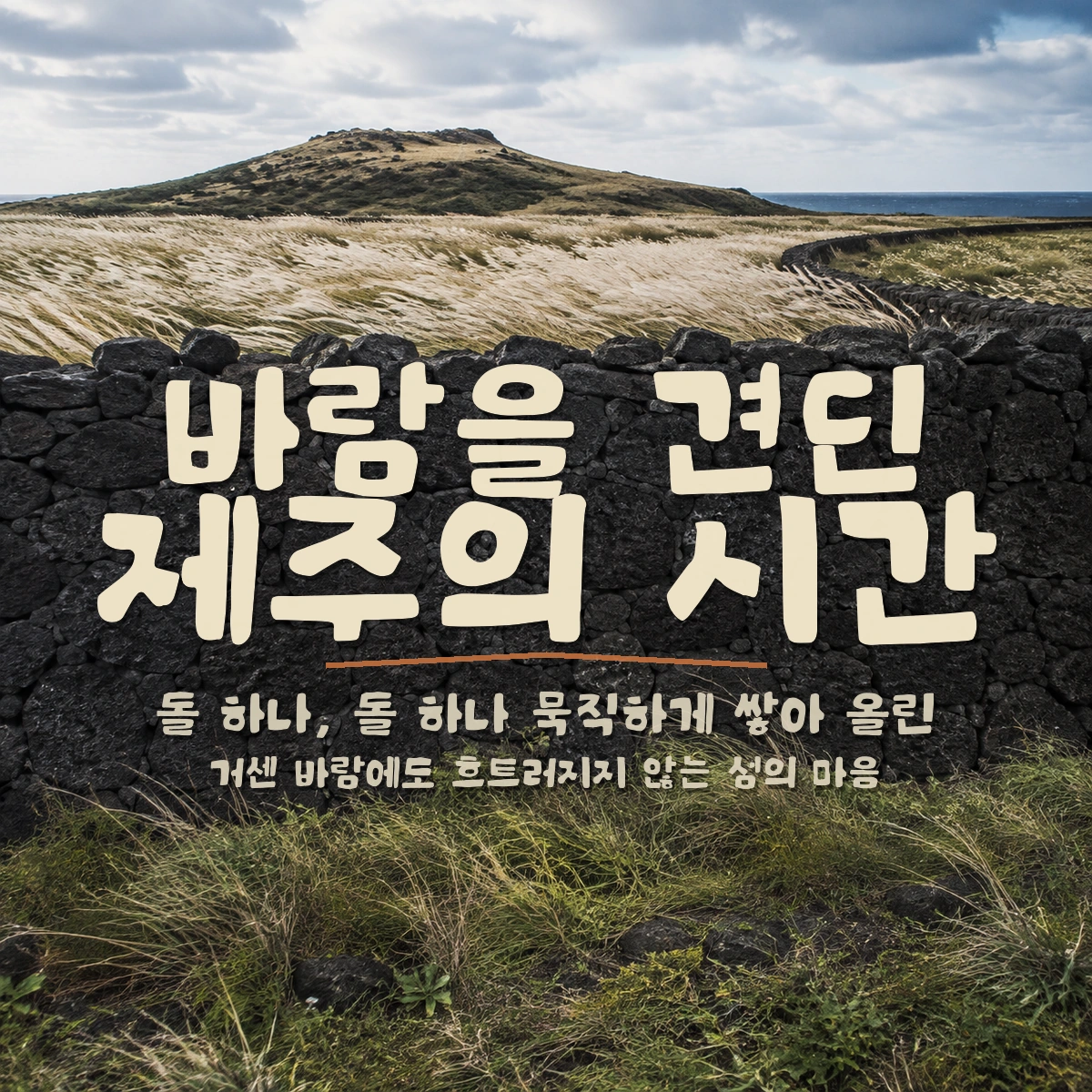
제주돌담체 — 얼리폰트에서 배포하는 무료 폰트입니다. 제주도의 돌담처럼 굵은 획을 어긋나게 쌓아 올려, 자유롭고 볼드한 인상을 내는 제목용 서체
얼리폰트가 배포하는 디스플레이 서체입니다. 모티브가 이름 그대로입니다. 제작자가 제주도에서 한 달을 살며 받은 영감을 담았고, 얼기설기 쌓인 제주도의 돌담처럼 자유롭고 볼드한 매력을 냈다고 밝히고 있습니다.
돌담의 불규칙함이 획에 들어가 있습니다. 파일에서 재어 보면 낱자가 가로로 넓게 퍼져 있고 자면을 넉넉히 채워, 굵은 돌이 어긋나게 쌓인 인상을 냅니다. 현대 한글 11,172자를 모두 담아 어떤 글자를 넣어도 빠지지 않습니다.